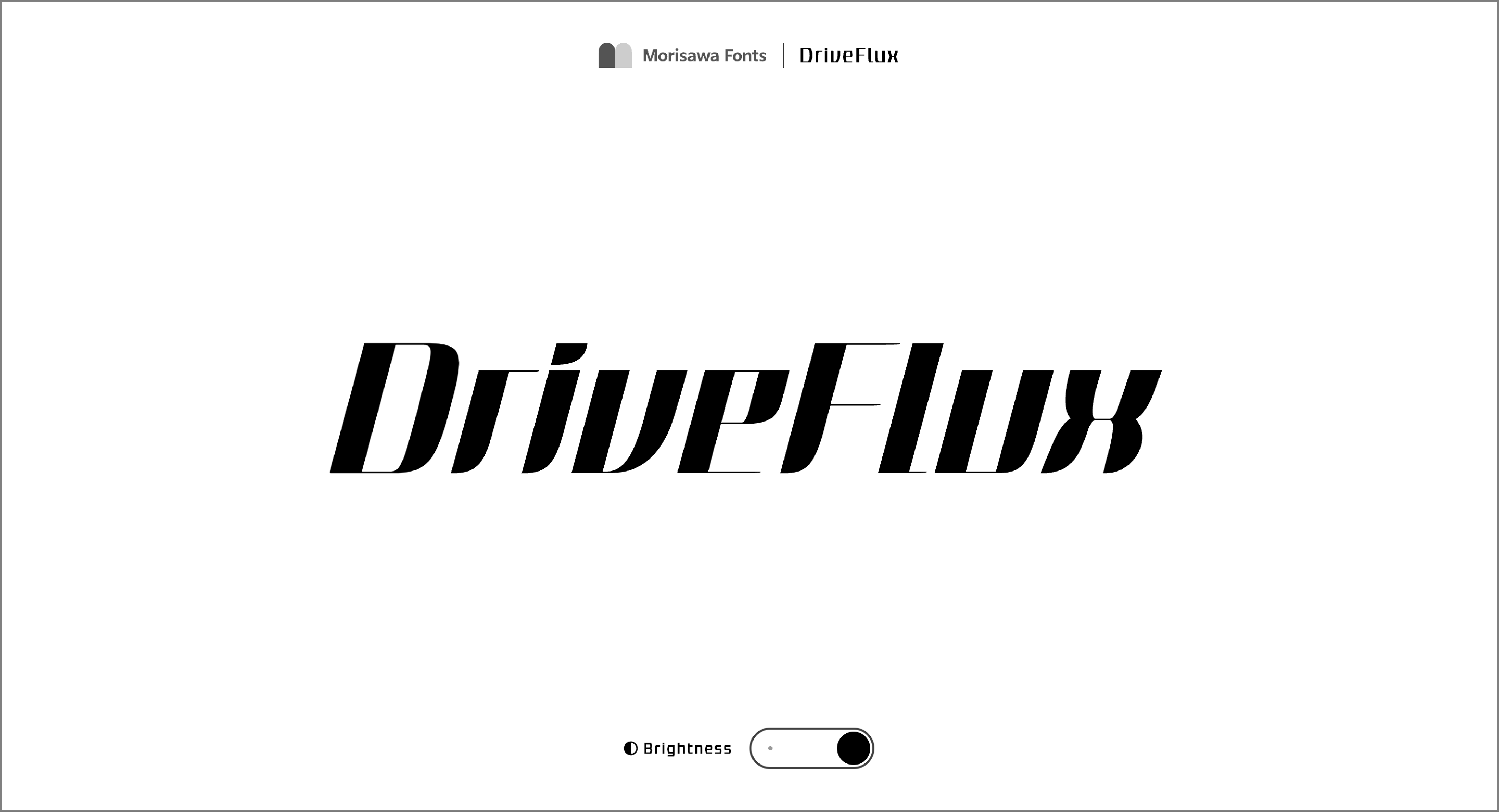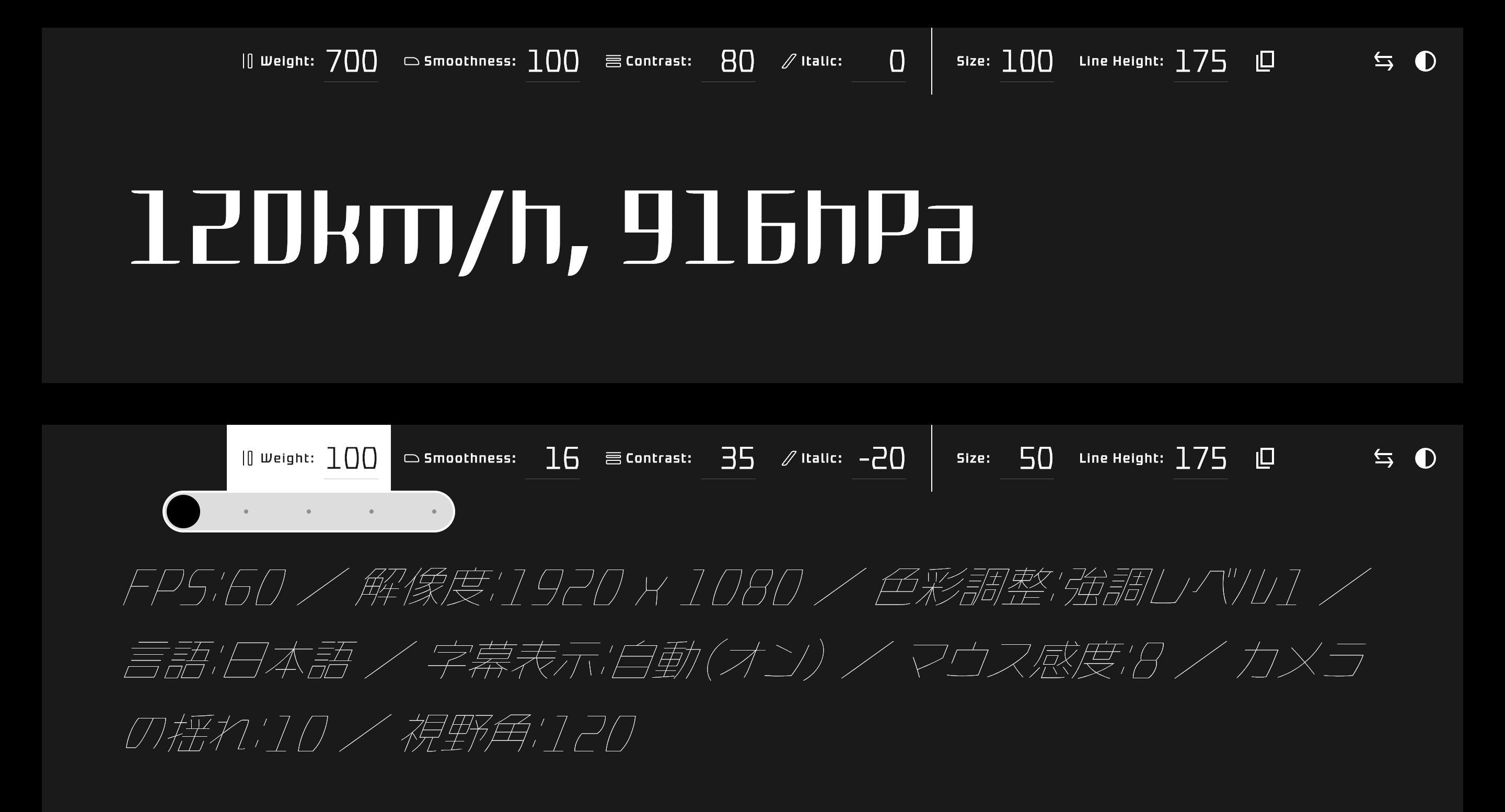
2024年度新書体第2弾をMorisawa Fontsにて提供開始
株式会社モリサワ(以下モリサワ)は2025年2月12日(水)より、Morisawa Fontsをご契約中のお客様に、Morisawa Fontsアップグレード2025年2月版として2024年度新書体第2弾の提供を開始しました。2024年10月にリリースした新書体第1弾に加えて、本アップグレードで追加された書体は合計37ファミリーです。
モリサワ初の和文バリアブルフォント「DriveFlux」をはじめ、ハングルのUDフォント「Clarimo UD KR」、インドと東南アジアの文字に対応した「Role Sans」多言語シリーズ、Occupant Fontsの欧文書体「Magmatic」や「Eggwhite」「Dispatch 2」など、多言語デザインの表現がさらに広がるラインナップを追加しました。
バリアブルフォント「DriveFlux」について
DriveFluxは、シンプルでシンメトリーな骨格と幾何学的なストロークで構成されたオンスクリーン向けの和文書体で、モリサワ初のバリアブルフォントです。太さを調整するWeight(ウエイト)、エレメントに流線型のカーブデザインを与えるSmoothness(スムースネス)、主に横画の太さを変化させるContrast(コントラスト)、傾斜角を調整するItalic(イタリック)の4つの可変軸を搭載し、多彩なデザインバリエーションを直感的かつシームレスに選択することができます。表現したいイメージに合わせて書体を動かし、自分だけのデザインを生み出せるDriveFluxが、映像やWeb上での新しい文字表現を実現します。